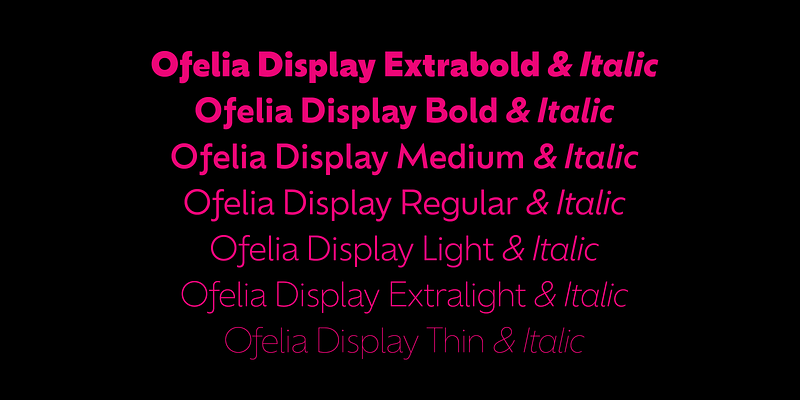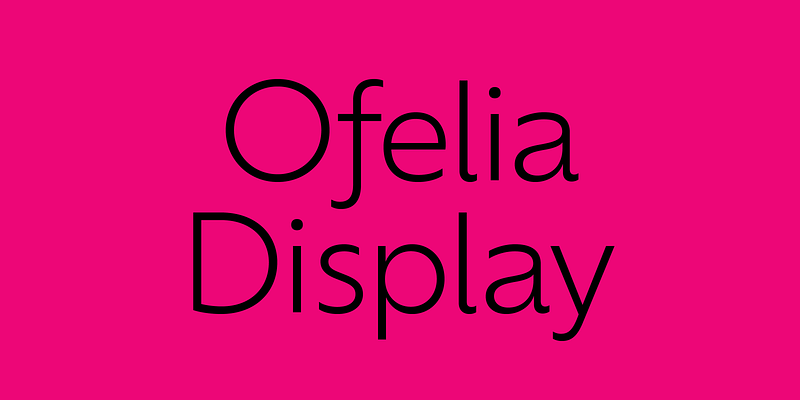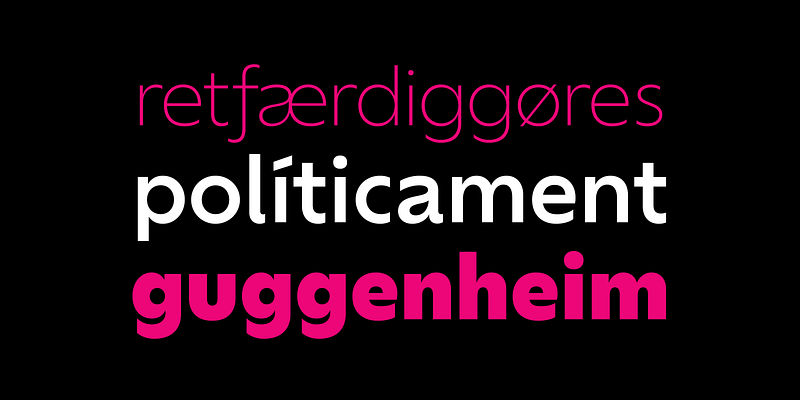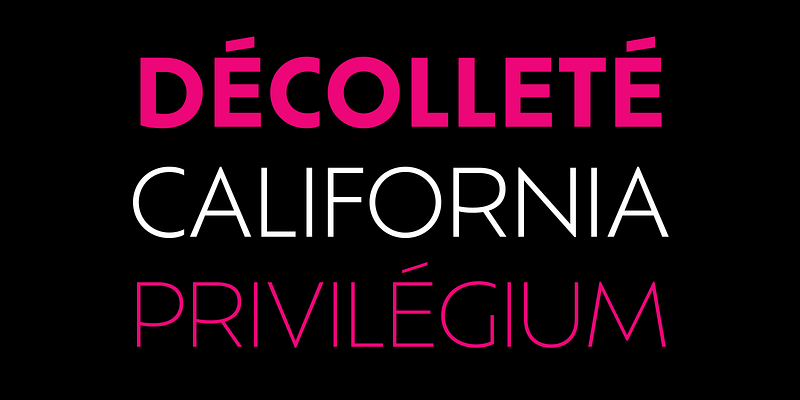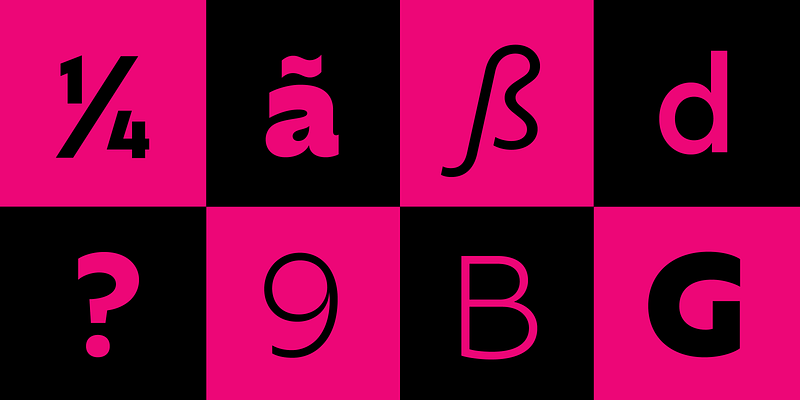
Ofelia est une typographie géométrique sans empattement adaptée à quasiment toutes les situations. Il s’agit d’une famille polyvalente de polices disponibles en deux tailles optiques, Display et Text, avec juste ce qu’il faut de personnalité. Ses caractéristiques géométriques évoquent la neutralité, tandis que des lettres comme /a, /f et la virgule lui apportent une touche gestuelle. Les polices disposent de petites capitales, de chiffres anciens et tabulaires, ainsi que de caractères alternatifs pour /a et /l.